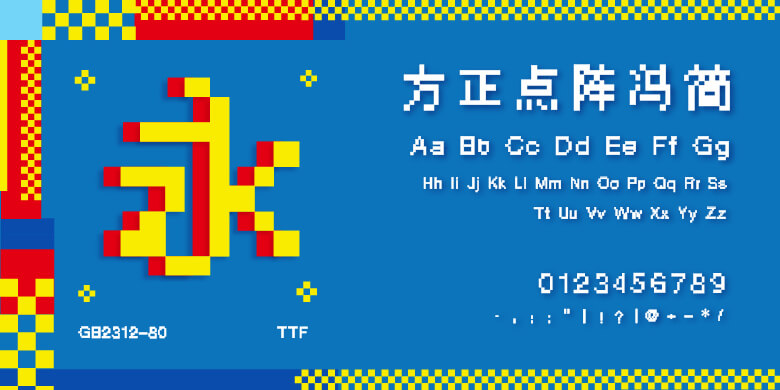
方正点阵冯
方正点阵冯的灵感来自古碑上已被磨蚀的文字。这款字体基于电脑点阵显示技术,通过调整像素的数量来模拟碑帖拓本中的极简字形,从而在可读和不可读之间达到平衡。黑色方块的组合代替所有笔画,并将字形结构简练到极致,感觉模糊抽象,让人联想到黑白、对错、得失、阴阳等对等概念的消长。方正点阵冯带有艺术实验性,古与今、人性与人工智能相互交融,可用来表达艺术和科技中一些观念性的文字。